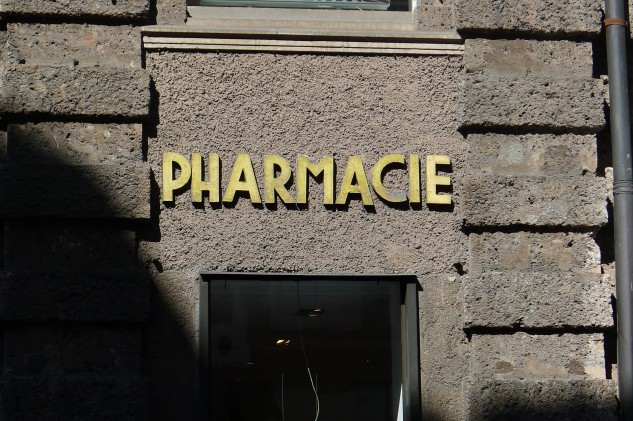
Pharmazie
Dort wo auch heute noch eine Apotheke ist haben wir diese wunderbare Schrift gefunden. Schmal und elegant wurde sie in die Fassade gesetzt, bekommt zwischen die beiden Pfeiler. Hier spielen Architektur und Typografie wunderbar zusammen, auch in den Farbnuancen.